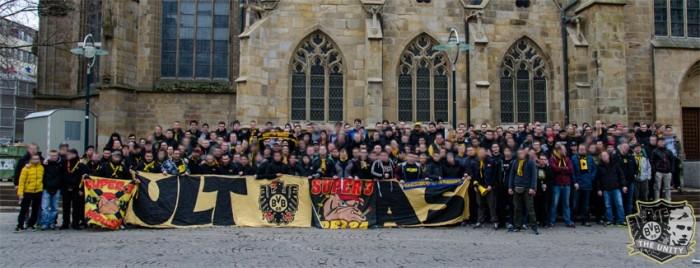
Suche die Schriftart der Zaunfahne?
Ich Suche schon seit längerem die Schriftart der ULTRAS Zaunfahne, vielleicht kann mir hier einer helfen.
das ist sicherlich einfach nur handgemalt. Ich wühle mal meinen E-Katalog nach ähnlichen Schriften durch ... Da finde ich zuerst mal nix so richtig passenden ...
Mein erster Tipp: Einfach nachmalen ... so es nur um das Wort ULTRAS geht.
Ich wühle nochmal durch den Katalog. Ich Suche nach einer serifenlosen Schrift in Extrabold oder Ultrabold oder Black oder Extrablack, Handwerk ... Alles zu weit weg. Ok, die Grobold, eine verrückte Kabel Black .. auch zu weit weg ... Schonan Black ... auch zu weit ... Tut mir leid für Dich, aber ich kann auf die Schnelle nix ähnlicheres liefern als: